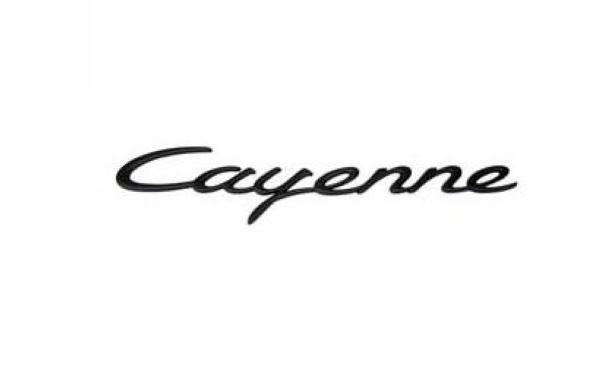
Porsche Cayenne
Hallo zusammen... ich suche eine Schrift, in Richtung Porsche "Cayenne" Logo (oder auch "Boxter").
Wenn es nur um eine ähnliche Schrift geht: Im Prinzip geht das in Richtung der Hooptie Script. Und wenn die noch nicht so richtig passt, dann ruf Dir die Hooptie doch mal bei MyFonts auf und lass Dir ähnliche anzeigen.  :-)
Vielen Dank für euren Einsatz... ne ne es geht nicht um das Logo selbst sondern um eine Schrift, die in diese Richtung geht. Also die "Damion" von BerndH ist schon ganz nah dran... damit kann man was anfangen... Danke!
...ja das "r" muss man etwas richten :-)